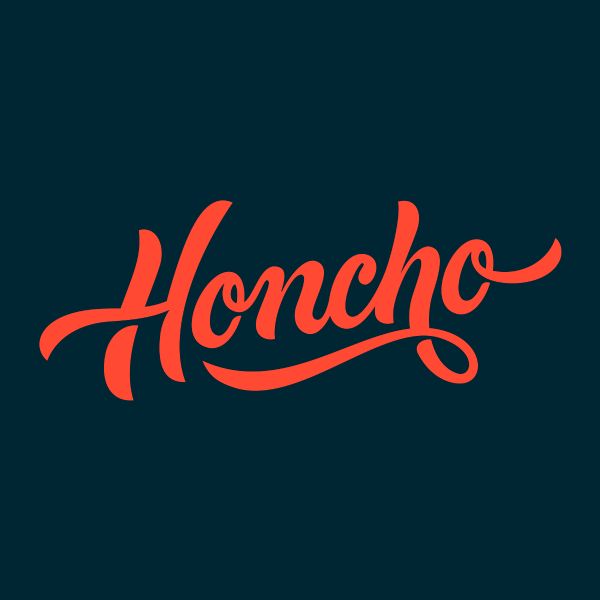
101 лучший бесплатный шрифт для создания логотипов
Когда вы работаете над созданием айдентики, используемый в логотипе шрифт — это один из ключевых элементов успеха проекта.
В эти моменты на помощь приходят бесплатные шрифты, которые наилучшим образом подходят для разработки логотипов.
Ниже представлен 101 шрифт, подобранный командой проекта Webdesignerdepot для создания логотипов.
BEAVER
TROCCHI
BEBAS NEUE
VAST SHADOW
CANARO
NORWESTER
ALLER
LORENA
POIRET
FACUNDA
ATVICE
POLARIS
VAGTUR
AILERON
RBNO2
SANSUS
GENTONA
RAMBLA
FENIX
HIPSTELVETICA
RECKONER
AINSLIE
KRAFTSTOFF
PROSTO
SANSATION
SIMPLIFICA
GHANDI SANS
SCRIBER
GARNATA
PLANER
LEAGUE GOTHIC
HALLO SANS
ECONOMICA
KAINE
FORUM
GEARUS
NOUGATINE
ODIN ROUNDED
PROZA